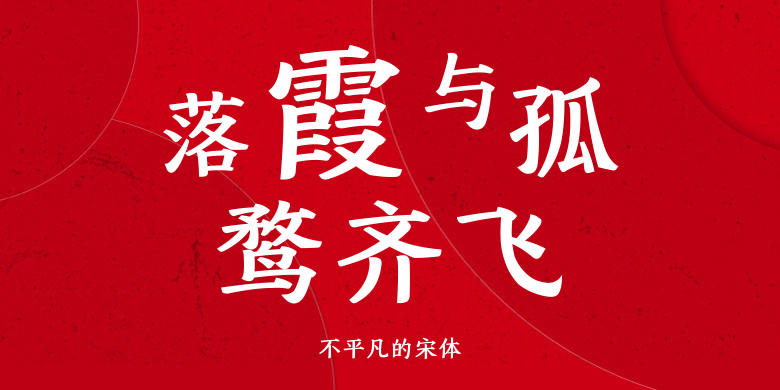
不平凡的宋体
不平凡的宋体,这款字体结构工整、笔画清晰,兼顾美观与易读性,适用于标题、正文、海报、包装、LOGO 等多种场景。字形优雅稳定,风格百搭耐看,适配日常排版与创意设计,让文字呈现更舒适、更具质感。不平凡的宋体一笔一画,皆是细节,以均衡的比例、流畅的线条打造舒适视觉体验,字形端正大气,风格简约现代。无论是商业设计、品牌宣传还是日常排版,都能轻松驾驭,让文字更有格调与力量。不平凡的宋体字体下载。